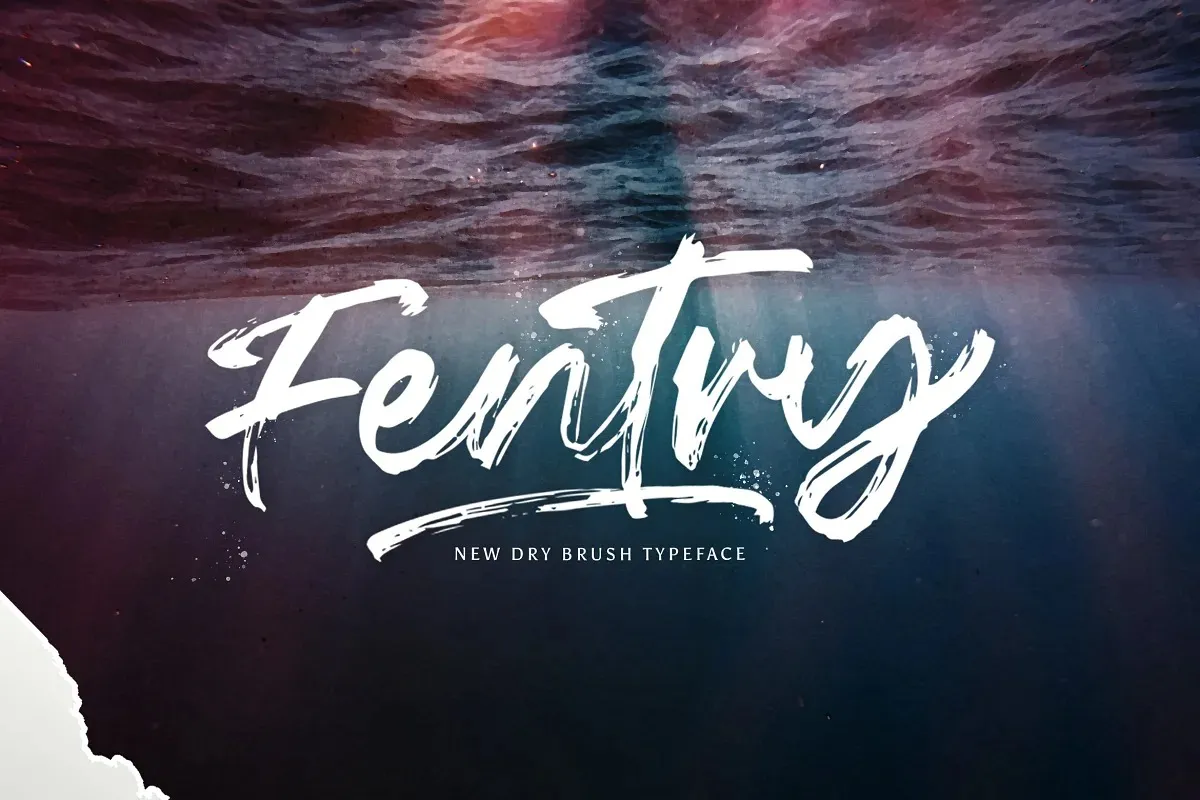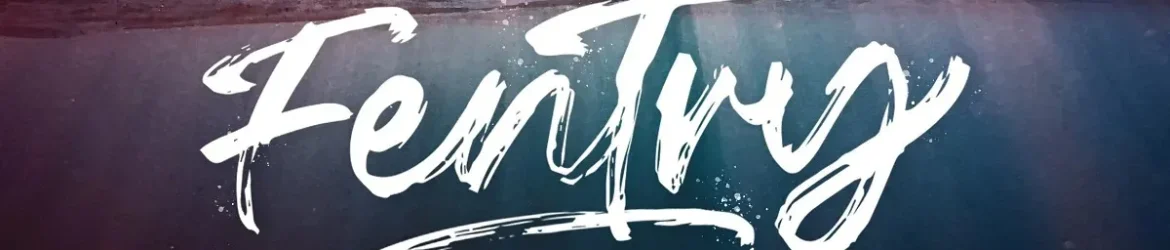
A Fentry Font é uma nova face a mão criada por StringLabs, perfeita para designers que buscam dar personalidade aos seus trabalhos visuais. Este tipo de letra pintura foi projetado especificamente como um script, ideal para o uso em diversas aplicações gráficas. Seja você um artista digital que busca criar selos para suas publicações, um profissional de design gráfico desejando adicionar um toque único aos seus trabalhos promocionais ou até mesmo um designer de moda buscando personalizar etiquetas e camisetas. Ou seja, a Fentry Font é uma opção versátil que pode ser usada para criar selos, cartas de visita, estampas, capas de livros, folders, cartazes ou qualquer outra coisa que precise de um toque personalizado. Aqui está o seu grande talento e criatividade na mão, sem esforço algum!